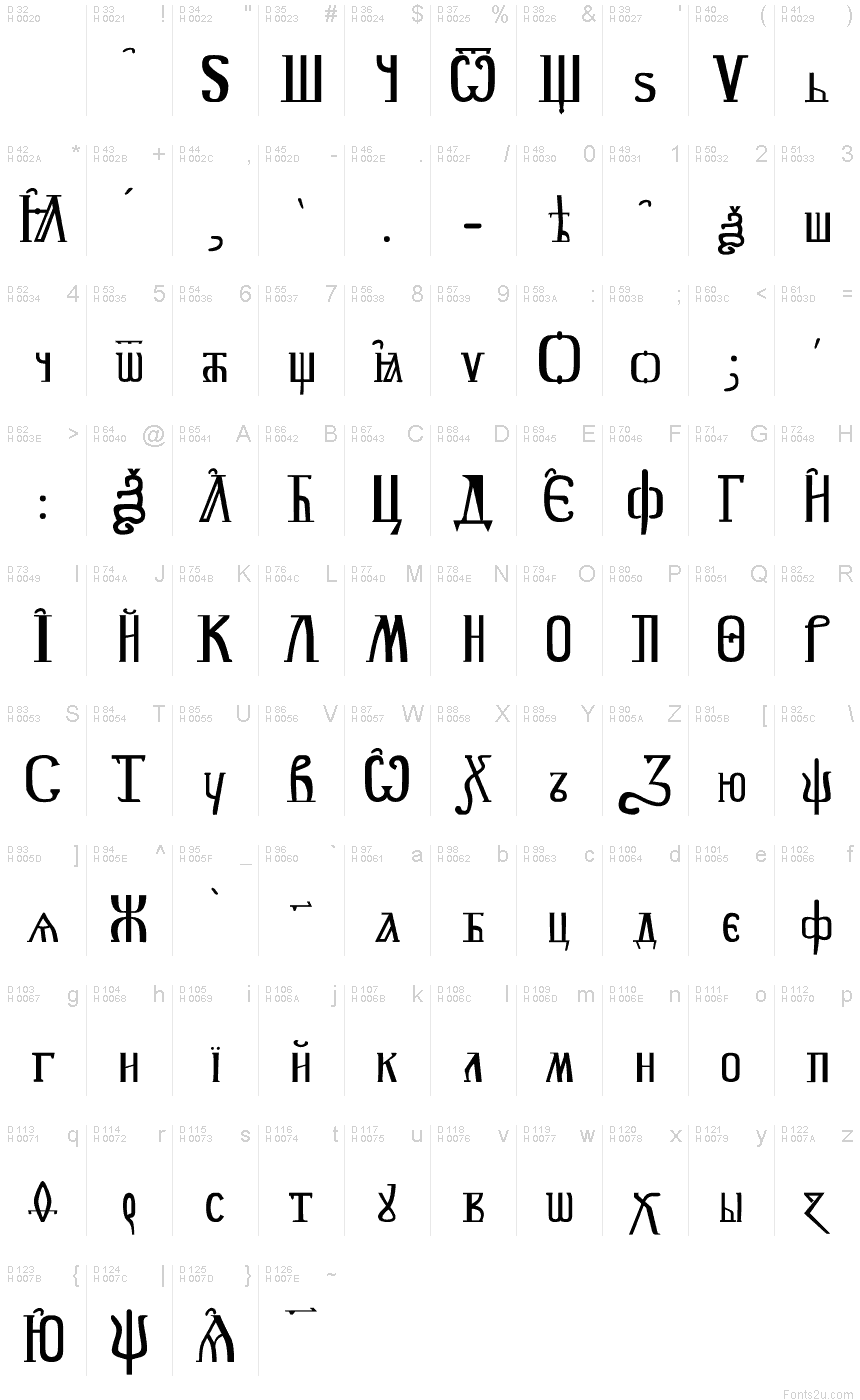
Pismotest, un font display cirillico gratuito di Typeface, porta con sé un’impronta tipografica slava distinta, caratterizzata da lettere alte con grazie e un ritmo letterario netto. Le forme uniscono verticali robuste, raccordi appuntiti e curve modulate, rendendo questo font più vicino alle pagine di libri antichi e alle testate dei giornali che alla neutralità della segnaletica moderna.
È la scelta naturale per manifesti culturali, copertine di libri, testate editoriali, grafiche per mostre storiche e titoli che richiedono un tocco d’epoca senza risultare puramente ornamentali. Essendo un font gratuito, è particolarmente indicato per titoli brevi, richiami in copertina e iniziali, dove le punte affilate e le grazie formali danno il meglio di sé.